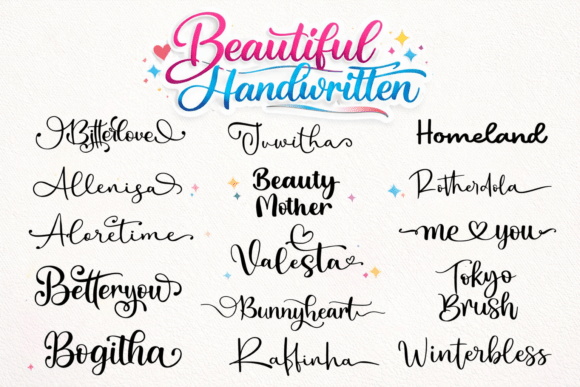
Beautiful Handwitten
์˜ฌ๋ฐ”๋ฅธ ๋””์ž์ธ ์š”์†Œ๋ฅผ ์ฐพ๋Š” ๊ฒƒ์€ ์–ด๋ ค์šธ ์ˆ˜ ์žˆ์ง€๋งŒ Beautiful Handwitten๋Š” ์ž‘์—…์„ ์ฆ‰์‹œ ํ–ฅ์ƒ์‹œํ‚ค๋Š” ๋›ฐ์–ด๋‚œ ์ปฌ๋ ‰์…˜์„ ์ œ๊ณตํ•ฉ๋‹ˆ๋‹ค.
POD(์ฃผ๋ฌธํ˜• ์ธ์‡„) ์ œํ’ˆ, ๊ฒฐํ˜ผ์‹ ์ดˆ๋Œ€์žฅ ๋˜๋Š” ์†Œ์…œ ๋ฏธ๋””์–ด ๊ทธ๋ž˜ํ”ฝ์„ ๋งŒ๋“ค ๋•Œ Beautiful Handwitten๋Š” ์ด์ƒ์ ์ธ ์„ ํƒ์ž…๋‹ˆ๋‹ค.